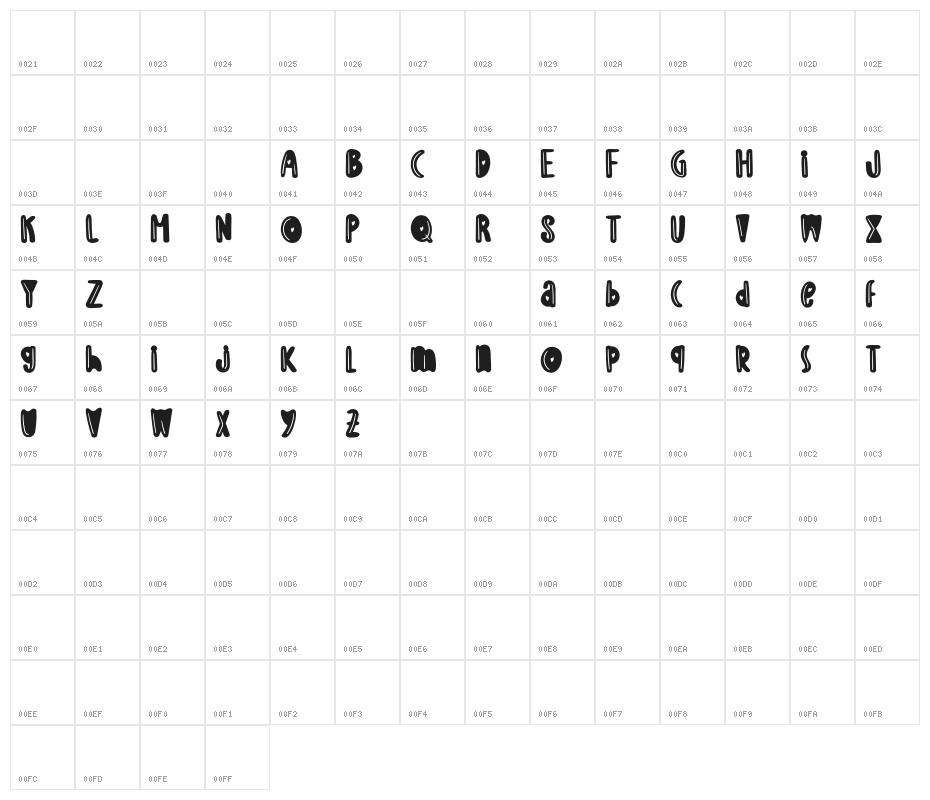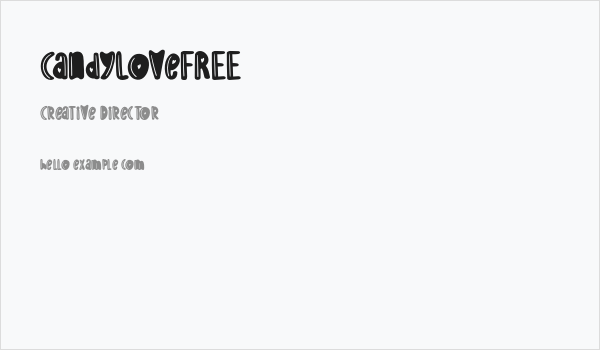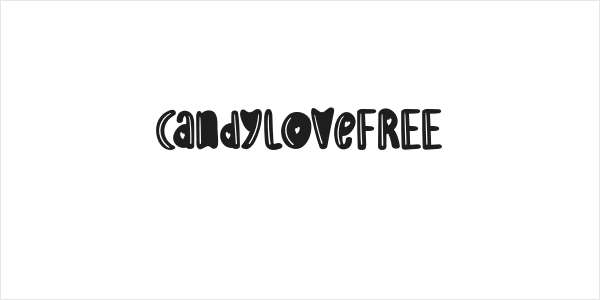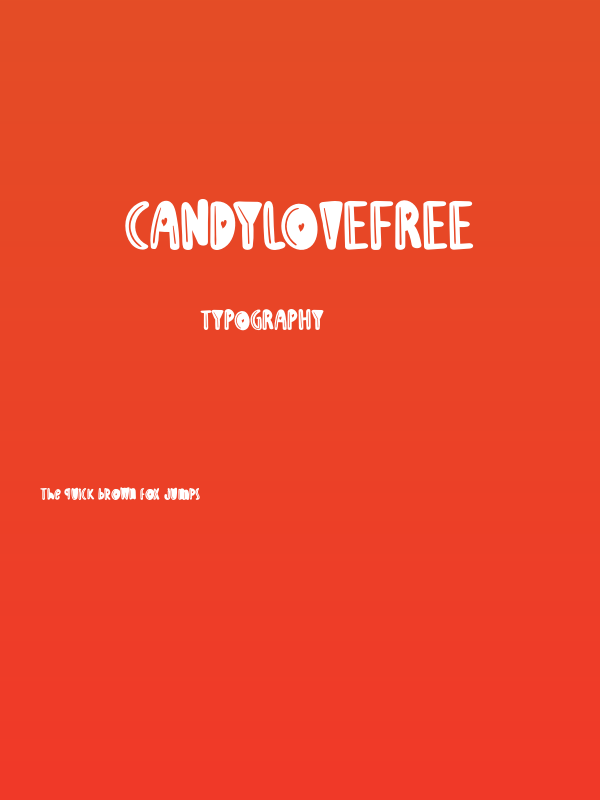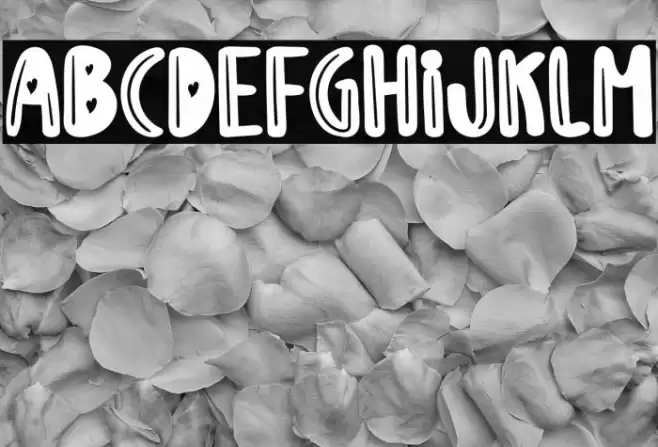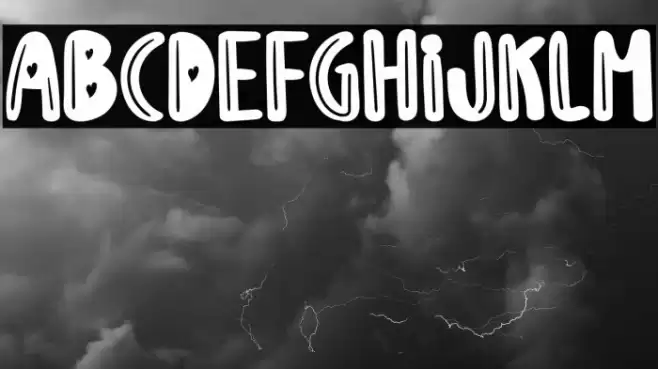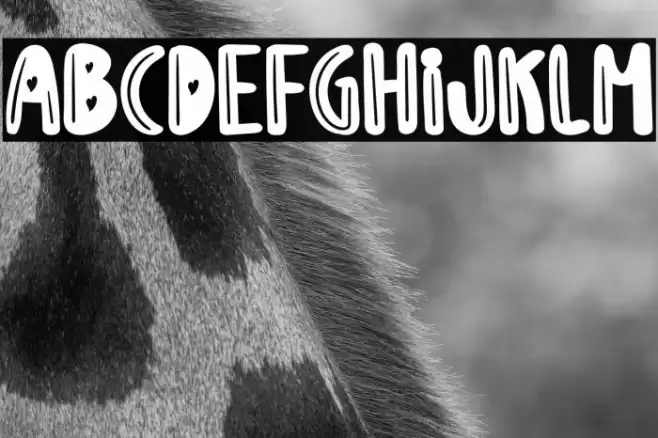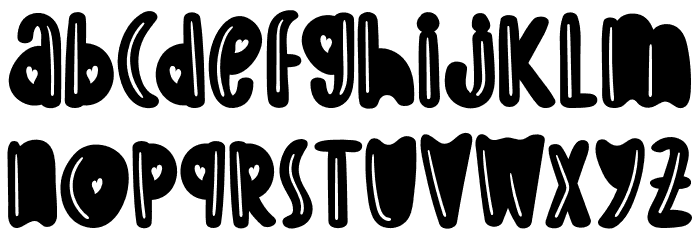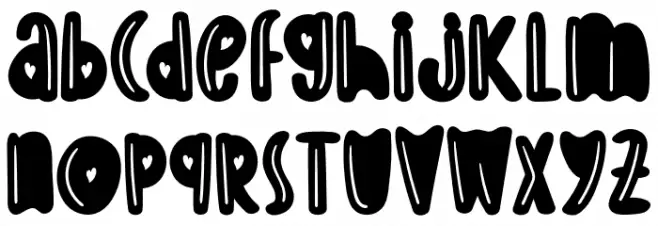
CandyLoveFREE Font
| Estilo general | Playful, Whimsical |
| Proyectos propuestos | Perfect for children's book covers, playful branding, party invitations, and greeting cards. |